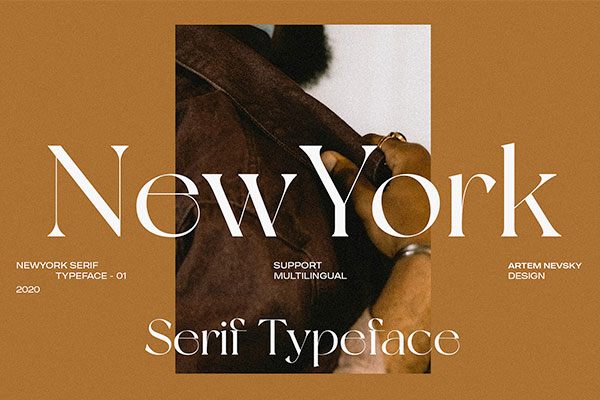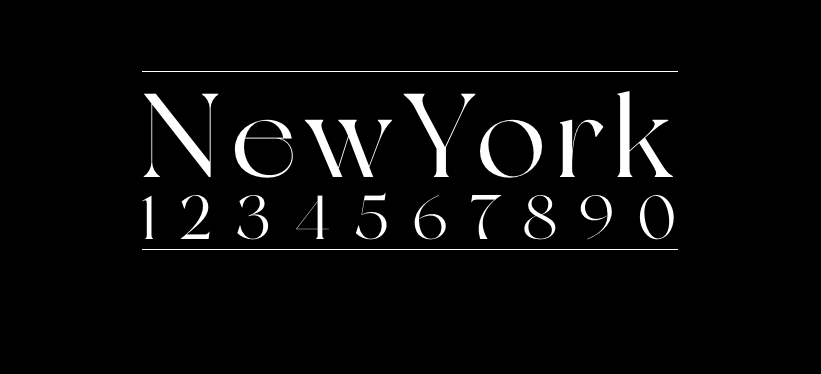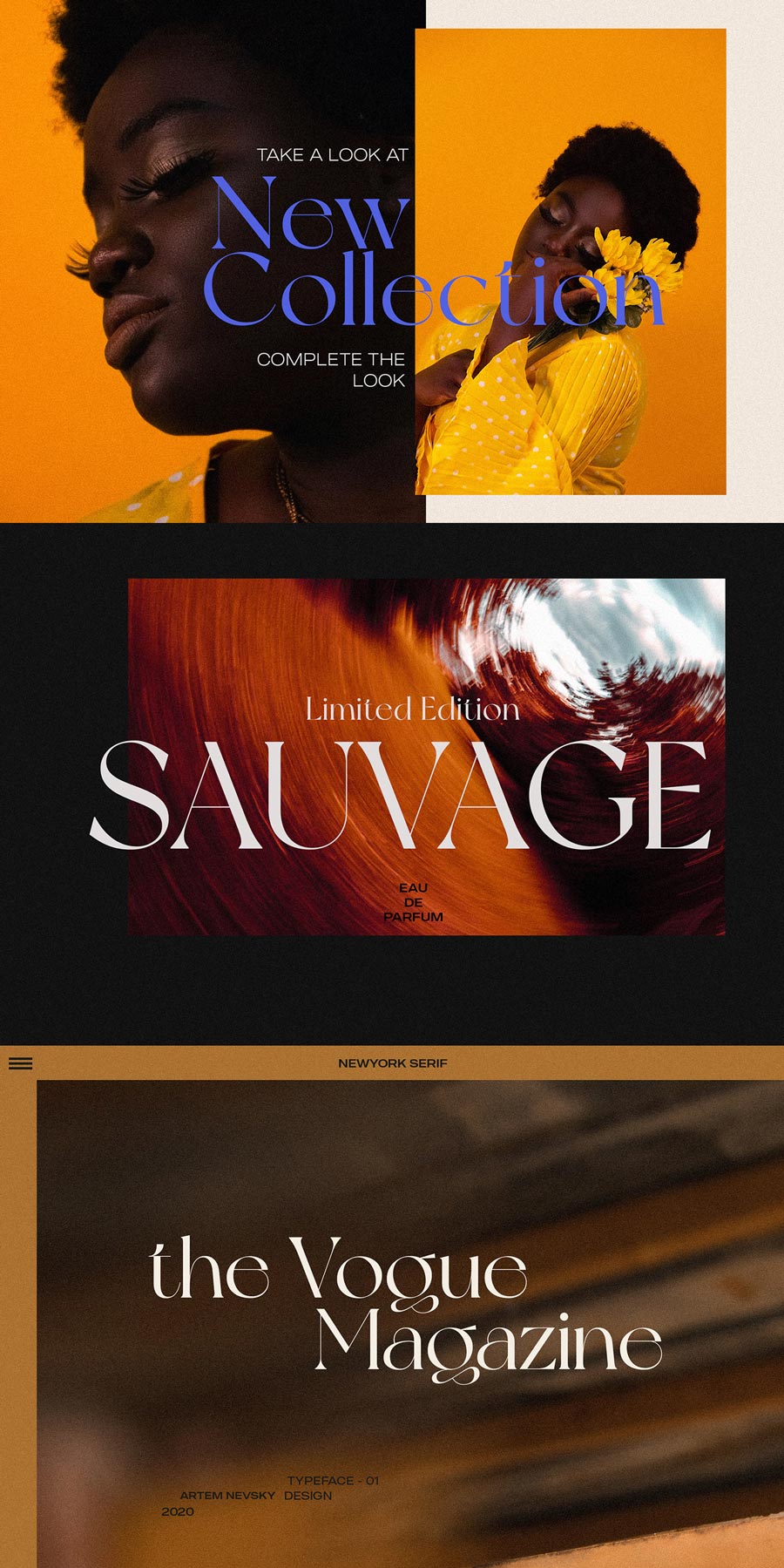
NewYork
NewYork字体介绍
NewYork字体的作者是来自俄罗斯的Artem Nevsky,NewYork字体是一款现代显示衬线字体,该字体最适合时尚,杂志,徽标和品牌,社交媒体和其他艺术品。NewYork字体首发于Behance,作者声明个人使用及商业使用免费。
NewYork字体应用示例